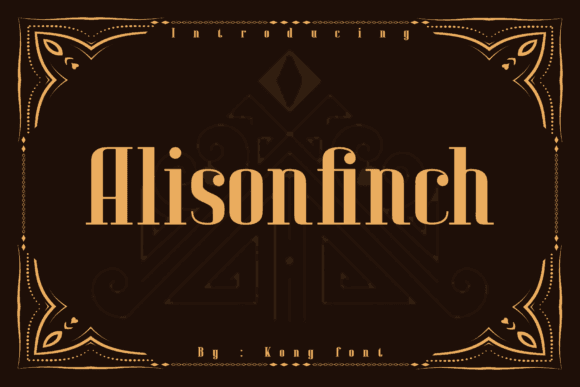
Fuente Alison Finch para titulares, carteles y proyectos de marca
Esta fuente serif profesional para display, diseñada para máxima claridad y presencia en textos de gran tamaño, ofrece elegancia tradicional con un equilibrio moderno, lo que la hace perfecta para encabezados y títulos visualmente impactantes.
Como fuente, Alison Finch está estructurada para una alta legibilidad y continuidad de diseño en identidades de marca, maquetaciones editoriales y recursos promocionales. Sus contornos limpios y espaciado proporcional brindan flexibilidad para una narrativa visual impactante.
Listo para elevar las narrativas visuales en plataformas de moda, estilo de vida, negocios y editoriales.
Lo que puedes hacer
- Gráficos de titulares y diseños de carteles
- Diseños de revistas y editoriales
- Logotipos, marcas denominativas y eslóganes
- Presentaciones y materiales de marca
- Banners digitales y elementos visuales para redes sociales
Por qué te encantará
- Serifa de estilo editorial para autoridad visual
- Ideal para marcas impresas y digitales.
- Legibilidad nítida en tamaños grandes
- Tono elegante con equilibrio funcional.
P: ¿Qué tipo de fuente es Alison Finch?
R: Alison Finch es una fuente serif de alto contraste diseñada para un uso impactante en displays, incluidos titulares, marcas y títulos editoriales.
P: ¿Puedo usar esto para logotipos y marcas?
R: Sí, Alison Finch es excelente para identidades de marca profesionales y tratamientos de logotipos.
P: ¿Incluye números y símbolos?
R: Sí, la fuente incluye un conjunto completo de caracteres con números y signos de puntuación básicos.
| Característica | Fuente Alison Finch | Editorial Serif A | Sans B moderna |
| Estilo de fuente | Exhibición elegante con serifas | Serifa clásica con contraste | Sans-serif neutral |
| Usos primarios | Titulares, carteles, branding | Diseño editorial y de libros | Interfaz de usuario web y móvil |
| Mejor característica | Tono editorial profesional | Equilibrio serif clásico | Sencillez y claridad |